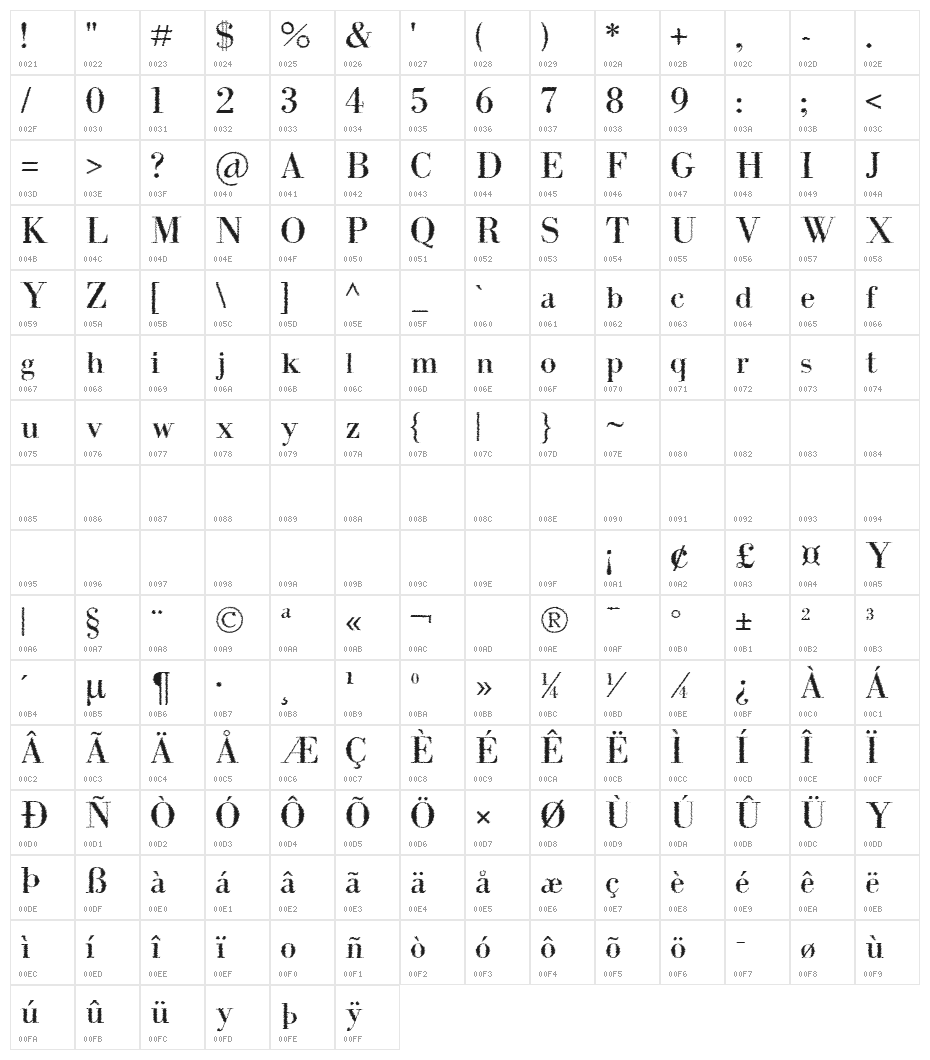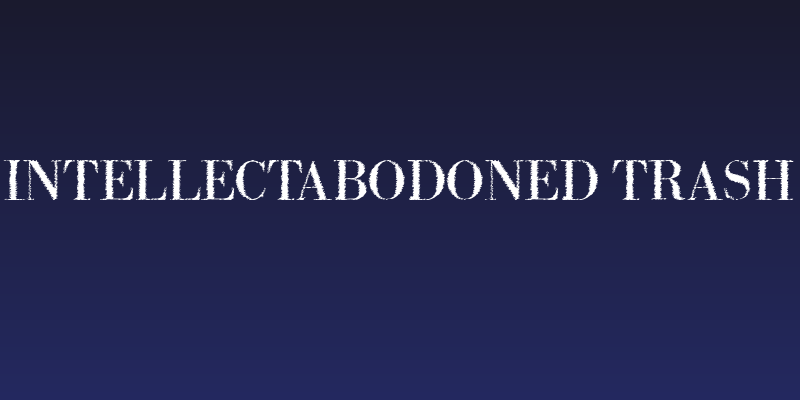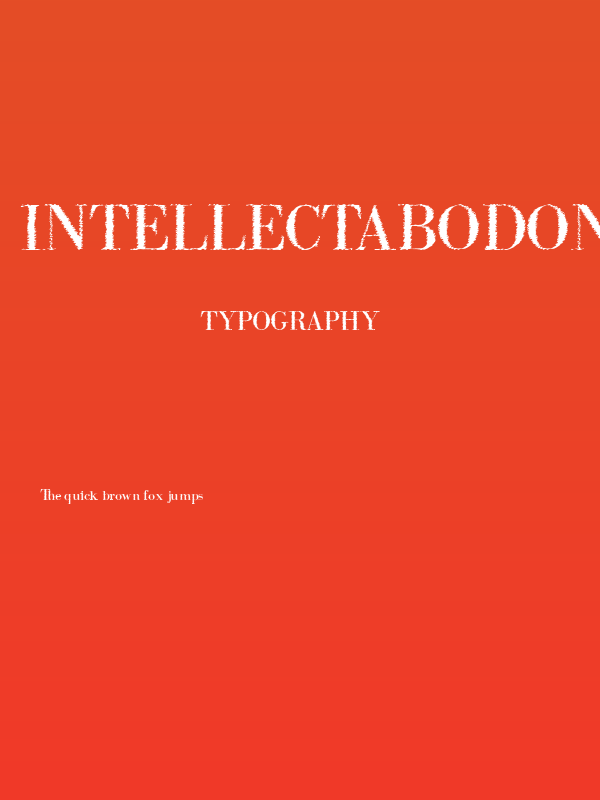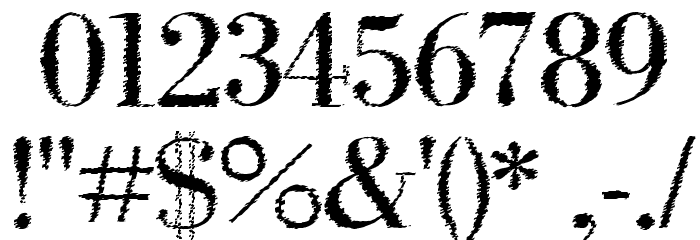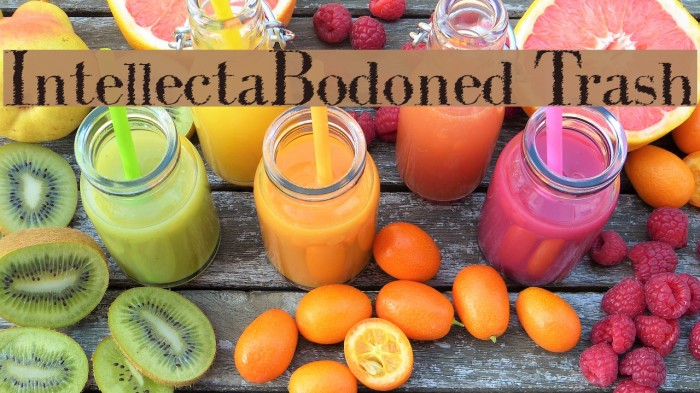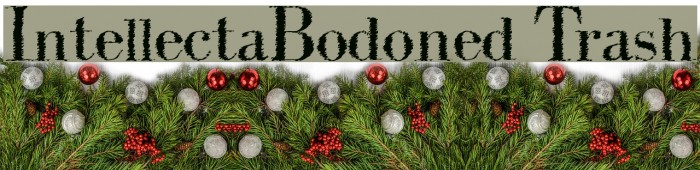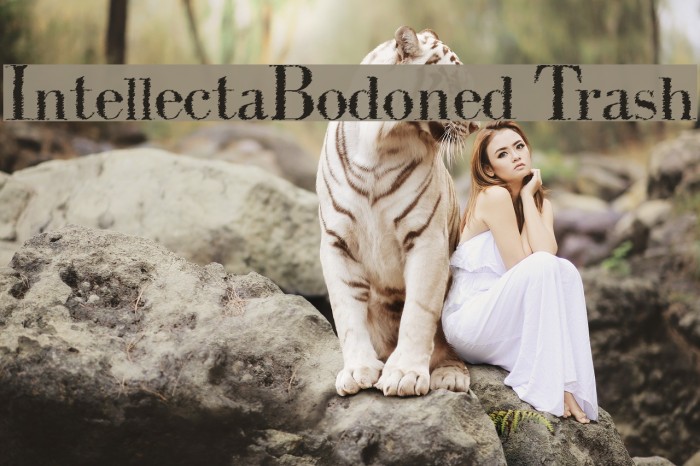
IntellectaBodoned Trash Font
✎ Distorted Eroded
| Kategorien | Distorted Eroded |
| Gesamtstil | Vintage |
| Anwendungsfall | Headlines, Logos, Decorative text |
| Vorgeschlagene Projekte | Ideal for vintage-themed designs, posters, album covers, and branding that requires a rustic or historical touch. |